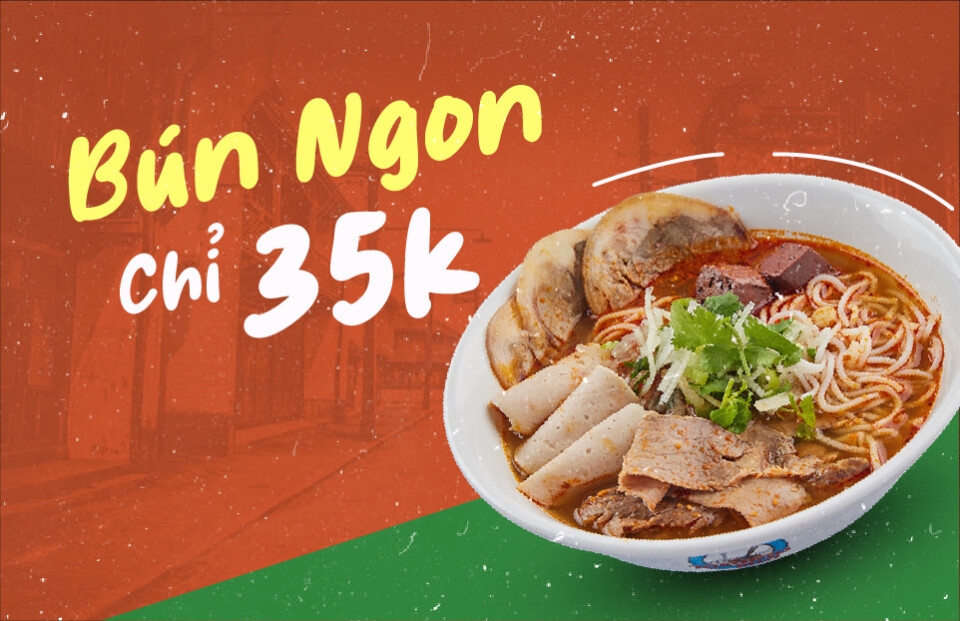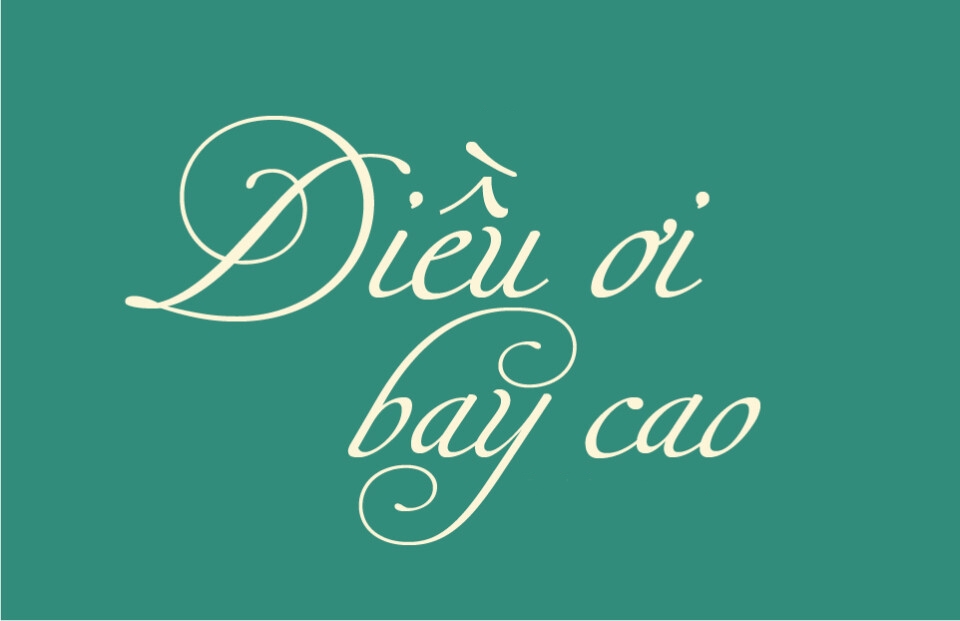
Tổng hợp 10 font chữ viết tay Việt hóa đẹp, tinh tế được sử dụng phổ biến nhất hiện nay
Font chữ viết tay thể hiện giá trị nghệ thuật cao nhưng vẫn toát lên sự tinh tế. Đây là một font chữ phổ biến trong thiết kế đồ họa, thiết kế bìa sách hay thiệp mời. Hãy cùng FPT Shop tìm hiểu 10 font chữ viết tay Việt hóa thông dụng nhất hiện nay qua bài viết này nhé!
Font chữ viết tay Việt hóa là gì?
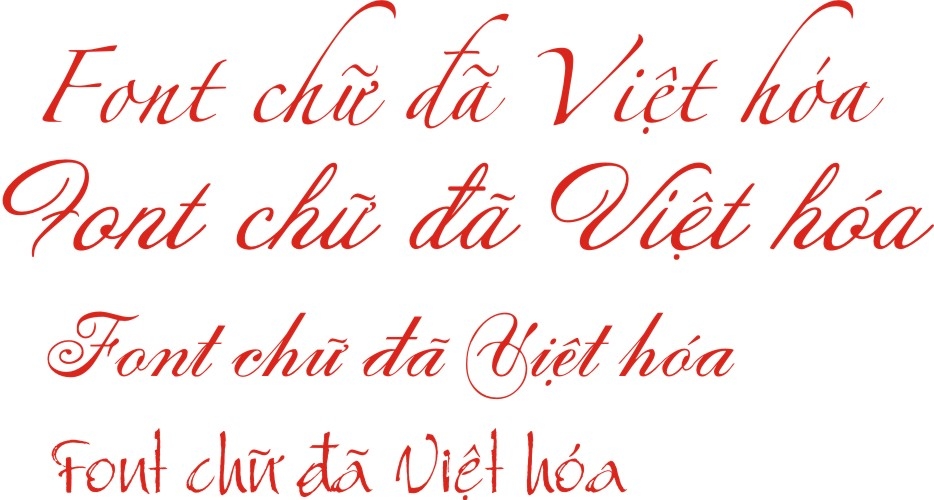
Font chữ viết tay Việt hóa được hiểu là loại font chữ được thiết kế riêng biệt để hỗ trợ tiếng Việt. Khi sử dụng các font chữ này để viết thì chữ cái, ký tự sẽ được chuyển đổi sang bảng mã Unicode giúp các chữ cái và ký tự không bị lỗi.
Tại sao nên sử dụng font chữ viết tay Việt hóa?
Font chữ viết tay Việt hóa được thiết kế theo những đường nét bay bổng và dành riêng cho người Việt. Ngoài ra, font chữ viết tay Việt hóa còn mang lại sự thân thiện, gần gũi so với chữ đánh máy thông thường.
Font chữ viết tay thể hiện được sự sáng tạo, cá tính riêng cho văn bản hay ấn phẩm truyền thông. Font có nhiều kiểu dáng, kích cỡ, phong cách khác nhau giúp bạn dễ dàng lựa chọn font chữ phù hợp với mục đích thiết kế. Nếu bạn yêu thích phong cách cổ điển, sang trọng có thể sử dụng font chữ viết tay với đường nét uốn lượn, mềm mại. Trong trường hợp bạn là người thích sự hiện đại, mạnh mẽ thì nên lựa chọn font chữ có đường nét khỏe khoắn.
Khi nào nên sử dụng font chữ viết tay Việt hóa?
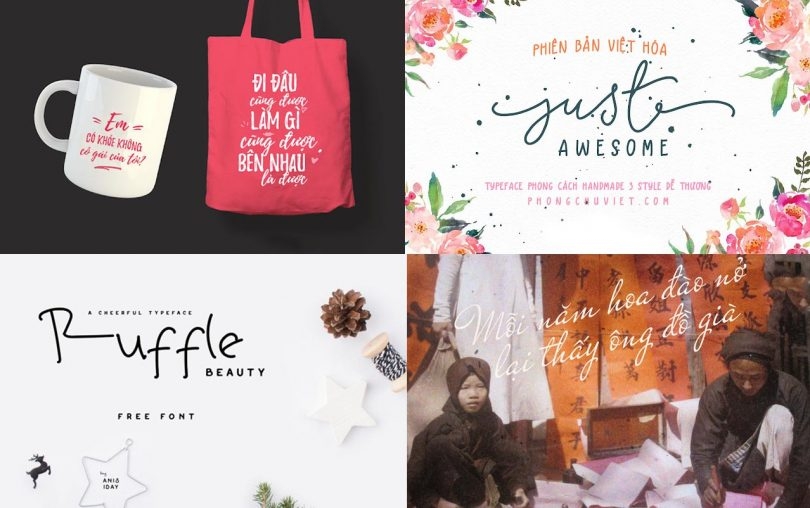
Thiết kế thiệp cưới, thiệp chúc mừng
Ưu điểm lớn nhất của font chữ viết tay Việt hóa là khả năng truyền tải cảm xúc đến người đọc. Đó là lý do font chữ viết tay chủ yếu được sử dụng trong việc thiết kế những tấm thiệp nhỏ xinh.
Thiết kế các ấn phẩm truyền thông Marketing
Font chữ viết tay Việt hóa sẽ giúp cho thông điệp của bạn trở nên gần gũi hơn trong mọi chiến dịch truyền thông. Các font chữ viết tay được Việt hóa sẽ tạo hiệu ứng thị giác cao hơn và để lại ấn tượng mạnh trong tâm trí người xem cũng như khách hàng.
Thiết kế nhận diện thương hiệu
Sử dụng font chữ viết tay Việt hóa trong thiết kế logo, banner, poster,… góp phần tạo sự nổi bật cho thương hiệu, từ đó giúp thương hiệu trở nên dễ nhớ, dễ gần với khách hàng.
Top 10 font chữ viết tay Việt hóa đẹp trong thiết kế đồ họa
Dưới đây là tổng hợp 10 font chữ viết tay Việt hóa đẹp giúp bạn tạo nên những tác phẩm nghệ thuật ấn tượng.
1. Font Việt hóa Fleur De Leah
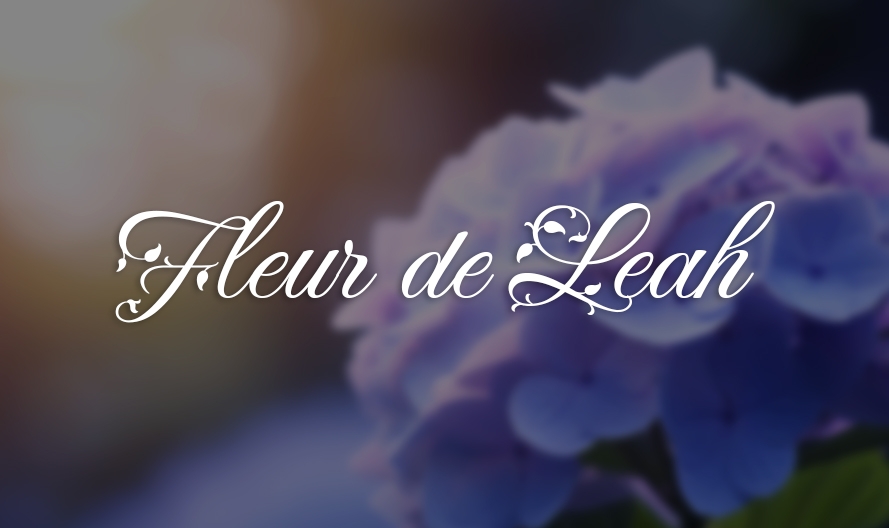
Leah Gaviota là tác giả của font chữ Fleur De Leah. Đây là mẫu font chữ tinh tế thuộc thể loại font chữ viết tay Việt hóa. Đặc biệt, font Fleur De Leah là sự kết hợp khéo léo giữa các yếu tố hoa lá và phong cách Art Nouveau, khiến cho cấu trúc chữ trở nên bay bổng và nhẹ nhàng hơn.
Font Fleur De Leah gồm 1 bảng đa dạng chữ hoa, chữ thường, số và các ký hiệu đặc biệt giúp bạn thoải mái sáng tạo. Font chữ phù hợp với các biểu ngữ, poster, thiệp mừng,… Vì vậy, nếu bạn là một designer hay một Marketer thì font chữ Fleur De Leah vẫn luôn là sự lựa chọn sáng suốt, hỗ trợ trong công việc của bạn.
2. Font Việt hóa Ephesis
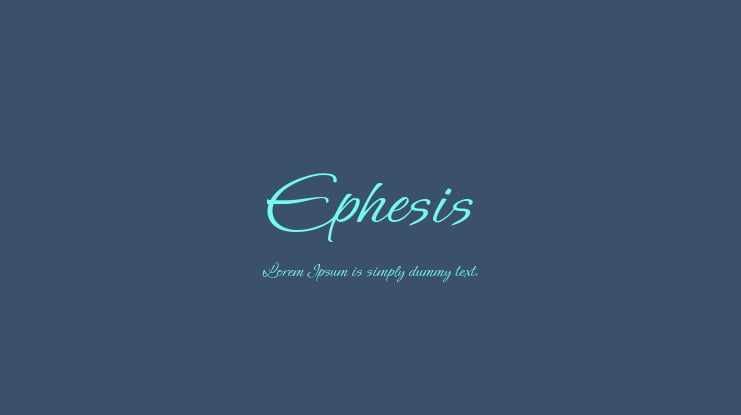
Nếu bạn là người yêu thích những gì mềm mại và hài hòa thì font Ephesis sẽ rất thích hợp để thể hiện phong cách này của bạn. Font phù hợp với nhiều loại hình thiết kế khác nhau. Đặc biệt trong các chiến dịch quảng cáo, loại font này sẽ mang lại sự gần gũi, thân thiện, từ đó tạo được thiện cảm trong mắt người xem.
3. Font Việt hóa Alex Brush
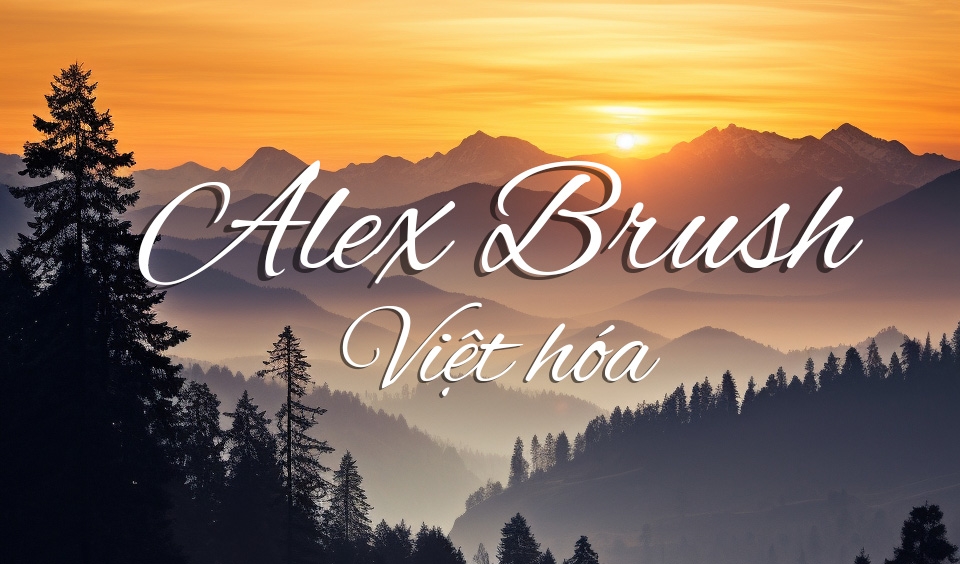
Font chữ Alex Brush không chỉ là font chữ viết tay thông thường mà còn là “chất xúc tác” tạo nên những tác phẩm nghệ thuật cuốn hút. Alex Brush hội tụ đủ sự tinh tế và quyến rũ để làm nên những tác phẩm sống động, chạm đến cảm xúc. Font chữ này sẽ gây ấn tượng với người xem ngay từ cái nhìn đầu tiên bởi sự mềm mại và uyển chuyển.
4. Font Việt hóa Agbalumo
Font chữ Agbalumo tạo sự khác biệt và nổi bật hơn cả nhờ nét chữ dày nhưng vẫn toát lên sự sang trọng cần có. Font chữ phù hợp trong mọi bối cảnh, từ thiết kế đồ họa đến văn bản trên các bài báo. Đường nét rõ ràng, dễ đọc sẽ giúp bạn thành công trong việc truyền tải thông điệp của nhà sáng tạo. Vì vậy, nếu bạn muốn tạo một thiết kế ấn tượng thì Agbalumo sẽ là font chữ hữu ích.
5. Font Việt hóa Shelia
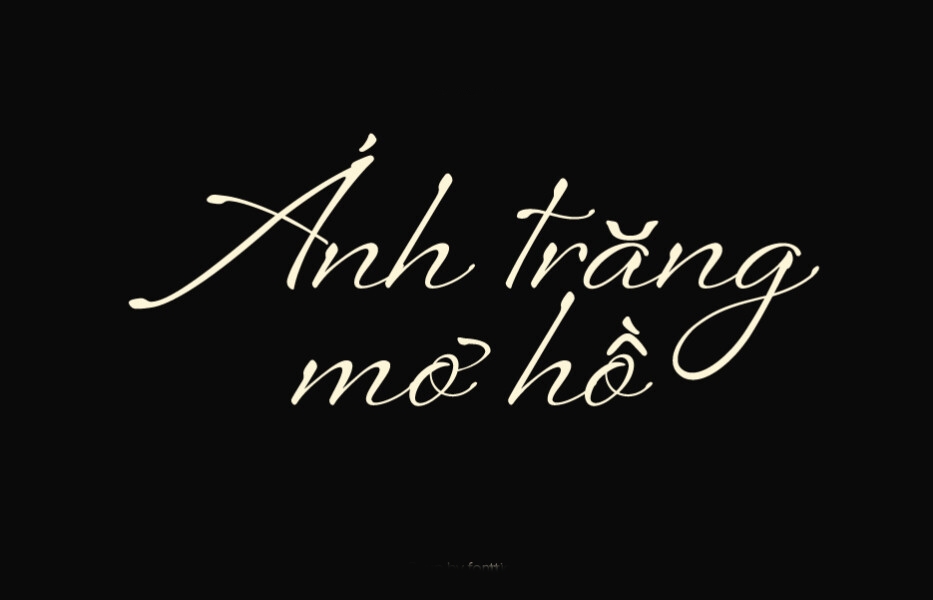
Font Việt hóa Shelia là kiểu font chữ đẹp mắt và có tính thời trang. Font chữ phù hợp với nhiều loại thiết kế, đặc biệt là thiết kế logo, trang bìa hay trang chủ website.
6. Font Việt hóa Yuong blood
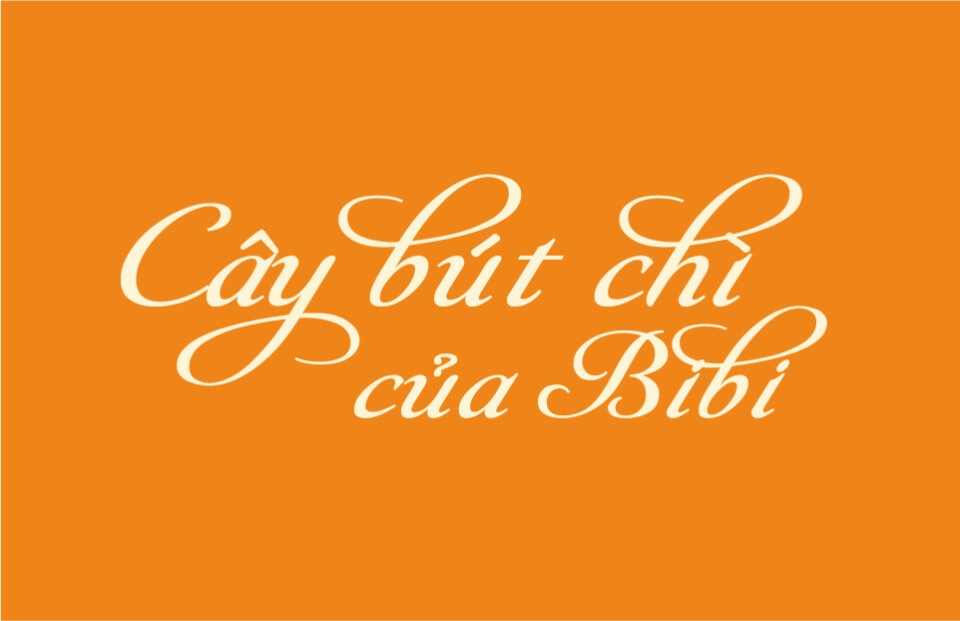
Font chữ viết tay Việt hóa Yuong blood là font chữ có các đường nét mềm mại, uyển chuyển tạo cảm giác dễ chịu, thư thái cho người nhìn. Font thể hiện phong cách thanh lịch, sang trọng mà không kém phần hiện đại. Font chữ Yuong blood phù hợp trong thiết kế thiệp mời, thiết kế logo, biểu trưng,...
7. Font Việt hóa 1FTV VIP Blacksword
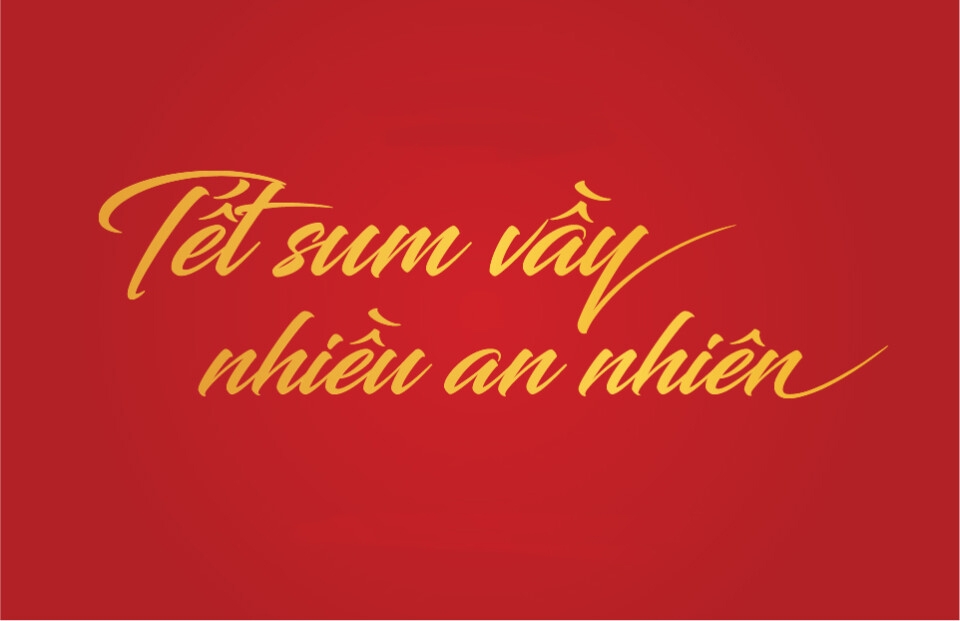
Nếu bạn đang tìm kiếm font chữ viết tay đẹp, độc đáo cho các ấn phẩm truyền thông trong dịp Tết đến xuân về thì không thể bỏ qua font chữ Việt hóa 1FTV VIP Blacksword. Font có các đường nét đậm nhạt rõ ràng, thiết kế in nghiêng cùng phần đuôi chữ kéo dài mang đến vẻ đẹp uyển chuyển và tinh tế cho tác phẩm nghệ thuật. Nhà thiết kế thường sử dụng font trong thiết kế lịch, thiệp mời chúc tết, banner ngày Tết,...